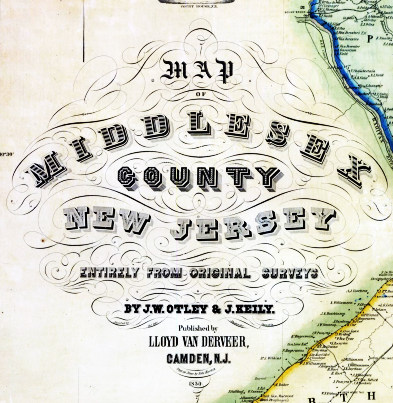
Dekorative Schriften 1850 - 1900
hat jemand Ideen für typische Schriften (Deko) zwischen 1850 und 1900?
Ich meine jetzt nicht Fraktur oder sowas sondern mehr Deko für Überschriften, Reklame usw.
Ist das nicht dann diese "Victorian Era"?
Beispiel:
vielleicht auch interessant:
Yves Peters beschreibt hier, wie man solche schriften selbst basteln kann.
hier eine Auswahl an Möglichkeiten: